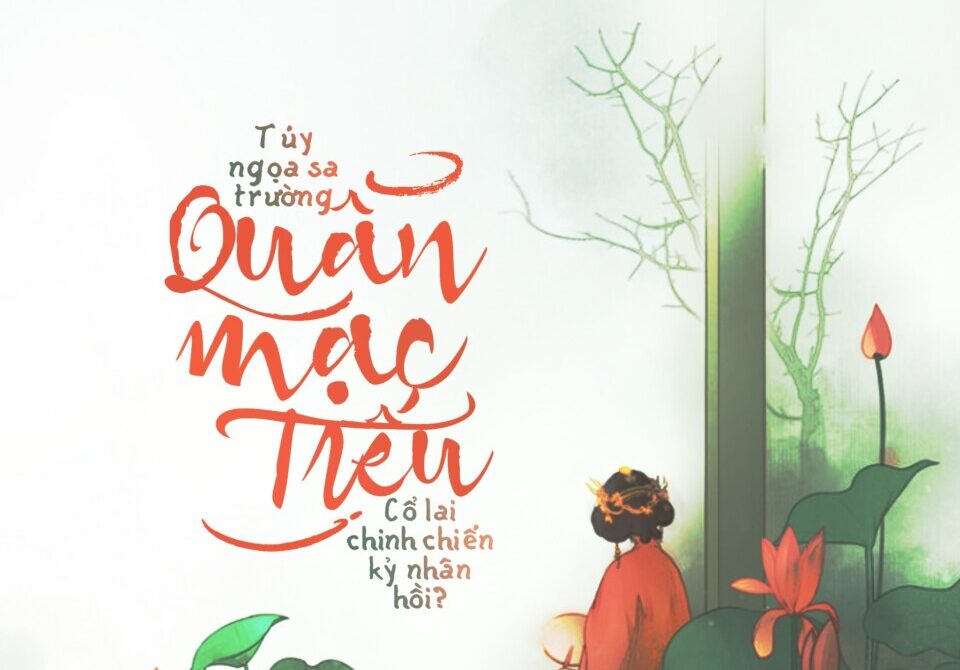
Khám phá vẻ đẹp cổ điển và sự tiện lợi của Font Việt hóa MTD Coffee Break Script
Trong thế giới thiết kế đồ họa, việc lựa chọn một Font Chữ phù hợp có vai trò quyết định đến cảm xúc và thông điệp mà tác phẩm truyền tải. Đối với cộng đồng thiết kế tại Việt Nam, nhu cầu về các bộ font đẹp và đã được Việt hóa hoàn chỉnh luôn ở mức cao. Và hôm nay, chúng tôi sẽ giới thiệu chi tiết về một tuyệt phẩm đang gây sốt: Font Việt hóa MTD Coffee Break Script. Bộ font script này không chỉ mang đến sự thanh lịch, mềm mại của nét chữ viết tay mà còn đảm bảo tối đa tính thẩm mỹ và chuyên nghiệp khi sử dụng các ký tự tiếng Việt. Đây là lựa chọn lý tưởng cho những dự án cần sự tinh tế và mang hơi hướng cổ điển, đặc biệt được ưa chuộng bởi sinh viên và các chuyên gia thiết kế đồ họa.
Font Việt hóa MTD Coffee Break Script: Tại sao lại được yêu thích?
MTD Coffee Break Script được thiết kế dựa trên cảm hứng từ những nét chữ ký cá nhân, mang lại cảm giác chân thực và độc đáo. Sự tinh tế trong từng đường cong, độ dày mỏng của nét chữ tạo nên một tổng thể hài hòa, rất phù hợp cho các thương hiệu cao cấp, thiệp mời sự kiện quan trọng hay các ấn phẩm đòi hỏi tính nghệ thuật cao. Phiên bản Việt hóa này đã giải quyết triệt để vấn đề lỗi hiển thị dấu tiếng Việt, vốn là rào cản lớn khi sử dụng các font quốc tế không hỗ trợ đầy đủ. Nhờ vào quá trình Việt hóa chuyên nghiệp, người dùng có thể hoàn toàn yên tâm về chất lượng hiển thị trên mọi nền tảng, từ in ấn tài liệu học tập cho học sinh, sinh viên đến giao diện website thương mại.
Sự phổ biến của font này còn đến từ tính linh hoạt của nó. Mặc dù là font script, MTD Coffee Break vẫn giữ được độ dễ đọc nhất định, không quá rối mắt như một số font viết tay khác. Điều này làm cho nó trở thành một công cụ mạnh mẽ trong tay các nhà thiết kế đồ họa, những người đang tìm kiếm một giải pháp Typography vừa đẹp mắt vừa thực dụng. Đặc biệt, nó thường được sử dụng trong các thiết kế liên quan đến cà phê, ẩm thực, và phong cách sống (lifestyle) – các lĩnh vực mà tính cá nhân hóa được đề cao. Font chữ này còn là một lựa chọn tuyệt vời cho các dự án tốt nghiệp của sinh viên cao đẳng, đại học.
Đặc điểm nổi bật và công nghệ của Font Việt hóa MTD Coffee Break Script
Đi sâu vào khía cạnh kỹ thuật, Font Việt hóa MTD Coffee Break Script nổi bật với bộ ký tự mở rộng (Extended Character Set). Bộ font này thường đi kèm với nhiều tính năng OpenType độc đáo như các chữ thay thế (Alternates), chữ nối (Ligatures) và các ký tự đầu cuối (Swashes). Các tính năng này cho phép người dùng tùy biến cách hiển thị của chữ cái, tạo ra những biến thể chữ viết tay phong phú và tự nhiên hơn, giúp bài thuyết trình hay đồ án trở nên sinh động và độc đáo hơn. Việc sử dụng các tính năng này yêu cầu phần mềm thiết kế chuyên nghiệp như Adobe Illustrator, Photoshop hoặc InDesign.
Quá trình Việt hóa không chỉ đơn thuần là thêm dấu. Nó bao gồm việc điều chỉnh khoảng cách giữa các chữ cái (Kerning) và đảm bảo các dấu thanh được đặt đúng vị trí, không chồng chéo lên nhau hay quá xa khỏi nguyên âm. Đối với MTD Coffee Break Script, đội ngũ Việt hóa đã làm rất tốt công việc này, giữ nguyên được tinh thần nghệ thuật của font gốc đồng thời tối ưu hóa cho ngôn ngữ tiếng Việt. Đây là yếu tố then chốt giúp font này trở thành một tài nguyên quý giá cho học sinh, sinh viên các ngành thiết kế cũng như các chuyên gia trong lĩnh vực truyền thông và Marketing.
Ứng dụng đa dạng trong các dự án của sinh viên và doanh nghiệp
Font chữ đẹp là một lợi thế cạnh tranh, đặc biệt trong các bài tập lớn hay đồ án tốt nghiệp của sinh viên. MTD Coffee Break Script thường xuyên xuất hiện trong các thiết kế poster, bìa sách, hay các dự án nhận diện thương hiệu. Ví dụ, một sinh viên ngành marketing có thể dùng font này để tạo ra logo cho một quán cà phê giả định, thể hiện sự ấm áp, cổ điển và chất lượng cao. Việc này không chỉ giúp bài tập đạt điểm cao hơn mà còn rèn luyện kỹ năng sử dụng font chữ một cách chuyên nghiệp, chuẩn bị cho kỳ thi tốt nghiệp quan trọng.
Ngoài ra, font script này còn là lựa chọn hàng đầu cho các ấn phẩm in ấn cá nhân như thiệp cưới, thiệp chúc mừng tốt nghiệp hay các thông báo quan trọng. Nét chữ mềm mại, bay bổng tạo cảm giác thân mật và trang trọng, phù hợp với không khí các buổi lễ tốt nghiệp cao cấp. Đối với các doanh nghiệp, việc sử dụng một font Việt hóa chất lượng cao như MTD Coffee Break Script giúp xây dựng sự nhất quán và chuyên nghiệp trong bộ nhận diện thương hiệu của họ, từ bao bì sản phẩm đến các tài liệu quảng cáo và báo cáo thường niên.
Sự chú trọng vào chi tiết nhỏ như cách font thể hiện các ký tự đặc biệt của tiếng Việt (như Ơ, Ư, Đ) đã làm nên tên tuổi của phiên bản Việt hóa này. Khi tìm kiếm các nguồn tài nguyên font chữ cho mục đích học tập hoặc kinh doanh, người dùng luôn ưu tiên những font chữ đảm bảo tính toàn vẹn ngôn ngữ, và MTD Coffee Break Script là một ví dụ điển hình về sự kết hợp hoàn hảo giữa phong cách thiết kế quốc tế và yêu cầu ngôn ngữ địa phương, mang lại sự yên tâm tuyệt đối khi sử dụng.
Tóm lại, Font Việt hóa MTD Coffee Break Script là một tài sản vô giá trong thư viện của bất kỳ nhà thiết kế nào. Với vẻ đẹp hoài cổ, tính năng mở rộng phong phú và sự tối ưu hoàn hảo cho tiếng Việt, nó xứng đáng là lựa chọn hàng đầu cho các dự án từ cá nhân đến thương mại. Việc đầu tư vào một bộ Font Chữ chất lượng không chỉ nâng cao tính thẩm mỹ của sản phẩm mà còn thể hiện sự tôn trọng đối với ngôn ngữ và người đọc. Hãy tải và trải nghiệm ngay MTD Coffee Break Script để mang lại sự khác biệt và đẳng cấp cho các ấn phẩm thiết kế của bạn, dù là bài tập ở trường hay một chiến dịch quảng cáo lớn.